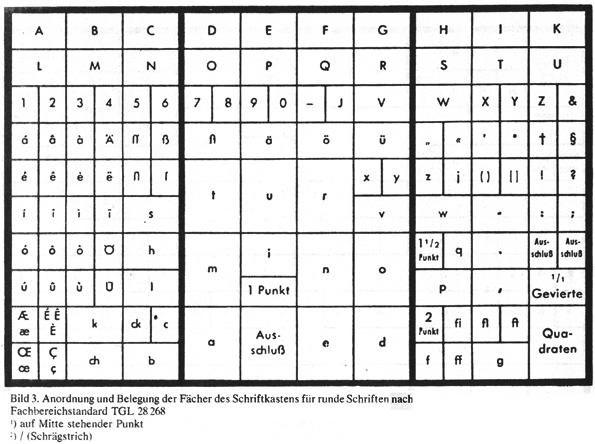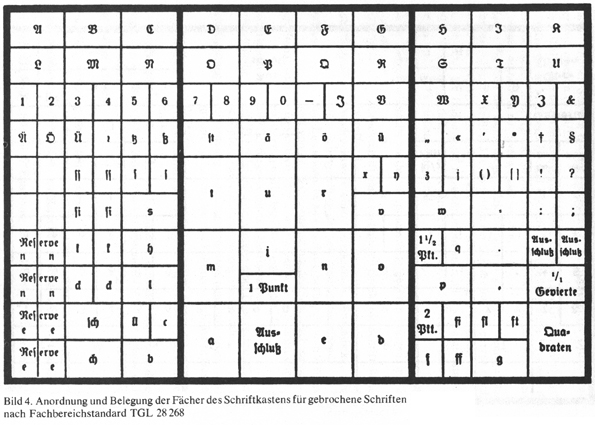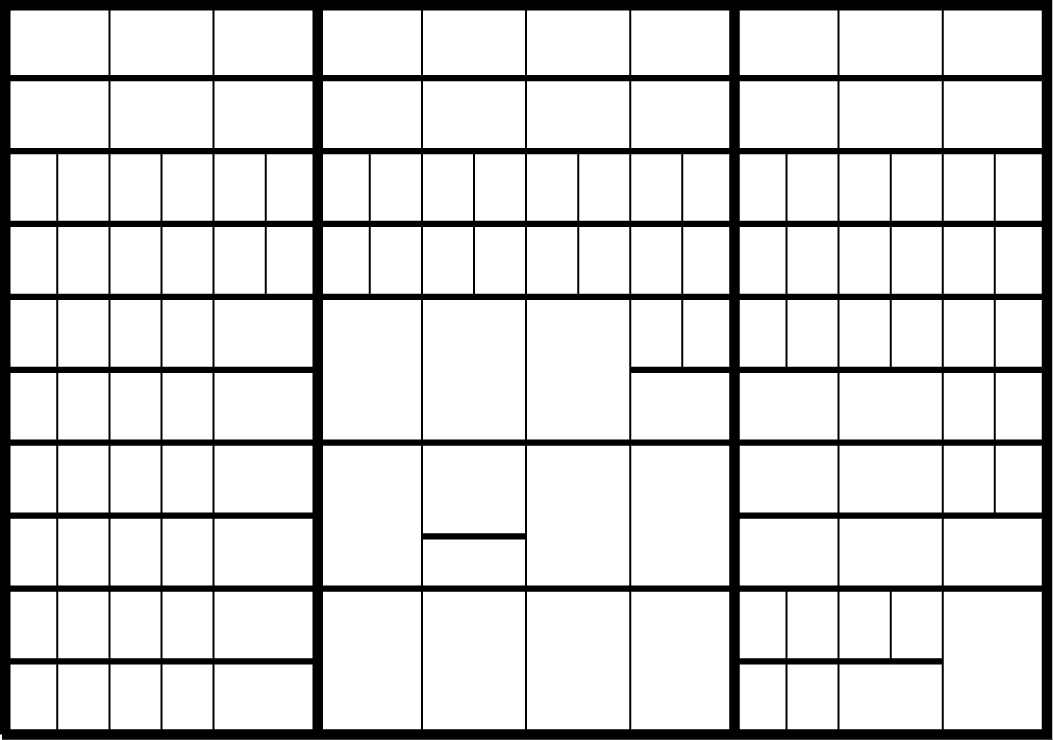
Setzkasten-Layout?
Kleine Frage an die Bleisetzer:
Wie allgemeingültig / verbreitet ist diese Setzkasteneinteilung (Wikipedia) – gibt es da viel Variantenspielraum, evtl. auch zwischen D / CH?
Habe heute im Brockenhaus einen Setzkasten gefunden, für etwa 13 Euro :cheer: .. Und der sieht anders aus als auf dem obigen Schema, siehe Bild. Beispielsweise sind die Kästchen, die im Bild mit »?t«, »ä«, »ö«, »ü« oder auch »W« bezeichnet sind, bei mir nochmal jeweils zweigeteilt; während andere, die im Bild zweigeteilt sind (z.B. 1½-Pt.-Spatium und q), bei mir nur aus einem Kästchen bestehen.
Würd mich interessieren, wenn hierzu jemand Näheres weiß, warum das vielleicht so ist oder so (Mann, ich bin vielleicht manchmal echt zu neugierig). Dranstehen tut übrigens »12 fette Antiqua«, falls das was zur Sache tut.
Grundsätzlich gibt es eine Vielzahl Varianten, auch wenn ich nicht weiß, ob nun ausgerechnet zwischen D und CH (na gut, man muß wohl berükchsichtigchen, daß man in der Chweitz einen gchößerchen Verchbrauch an ch-Ligchaturchen chat, dafür wenigerch ß brchaucht). In der Schweiz wäre weiters zu berücksichtigen, daß es da ja auch andere Landessprachen als das Deutsche gibt, und natürlich hat jede Sprache andere Kastenbelegungen, manchmal sogar eine extrem andere Kastenarchitektur. (Ich habe gerade mal gestöbert und bin erstaunt, was für kuriose Fremdsprachenkästen es doch gegeben hat; ich habe Setzkastenschemata für Sprachen gefunden, von denen ich noch nie etwas gehört habe.)
Und dies ist nur die Theorie. In der Praxis hat es in jeder Setzerei bestimmte Gepflogenheiten gegeben und auch die Setzer selbst haben sich die Kästen an ihre persönlichen Präferenzen angepaßt. Die kleinen Holzstege, die die Fächer unterteilen, sind bei trockener Luft manchmal geschrumpft und einfach aus der Nut gefallen. Als Setzer hatte man einen kleinen Vorrat an solchen Hölzern, mit denen man bei Bedarf Kästen weiter unterteilte. Das ging aber notfalls auch mit zurechtgeschnittenen Regletten oder Bleilinien.
Auch war der vorhandene Zeichenumfang je Schrift unterschiedlich, denn es gab zwar den Normal-Gießzettel, aber eben auch Abweichungen der Gießereien hiervon, die wiederum den Setzer zu individuellen Anpassungen des Schriftkastens zwangen.
Wenn man so ein Arbeiten gewöhnt ist, fallt es natürlich schwer, daß einem heute die Softwarefirmen verbieten wollen, sich seinen Setzkasten nach Gutdünken zu belegen — will meinen: Schriften zu editieren und sich die Zeichen auf die Tasten zu legen, die einem bequem erscheinen.
Übrigens: Wenn man sich z. B. die Frakturschriften der Fa. Delbanco ansieht, wird man feststellen, daß es auch heute abweichende Meinungen über die »richtige« Setzkasten- bzw. Tastaturbelegung gibt. Die haben ein ganz abenteuerliches eigenes Belegungsschema entwickelt. Es ist also alles wie früher: Es gibt eine DIN einerseits und es gibt die Praxis andererseits.
Hier mal Antiqua- und Frakturkasten nach TGL (Technische Güte- und Lieferbedingungen der DDR, sozusagen die Ost-DIN). Man beachte, daß auch im Antiquakasten ganz selbstverständlich ch, ck, Lang-s und die Lang-s-Ligaturen vorgesehen waren (jawoll, Herr Herrmann!).
… man muß wohl berükchsichtigchen, daß man in der Chweitz einen gchößerchen Verchbrauch an ch-Ligchaturchen chat, dafür wenigerch ß brchaucht).
In der Schweiz wäre weiters zu berücksichtigen, daß es da ja auch andere Landessprachen als das Deutsche gibt, und natürlich hat jede Sprache andere Kastenbelegungen, manchmal sogar eine extrem andere Kastenarchitektur.
Das könnte den Unterschied wohl zu einem Großteil erklären. Was interessant ist: Der DDR-Antiquakasten von Dir deckt sich fast ganz genau mit demjenigen aus der Wikipedia. Meiner weicht u.a. in den o.g. Details davon ab, und er sieht nicht so aus, als seien Stege manuell entfernt oder dazugefügt worden (hab leider grad keine Kamera da).
Dann ist meiner vielleicht wirklich ein Schweizer Modell. Zumindest müsste er, der Beschriftung entsprechend, aus einem deutschsprachigen Land kommen.
Mal schauen, ob ich irgendwann einen Schweizer Schriftsetzer kennenlerne, den ich das fragen kann. :)
An meiner Hochschule gabs zwar eine Handsatzwerkstatt, aber wir durften gerade nicht rein. (»Sie sind Multimediadesigner, beschäftigen Sie sich lieber mit der 32-bit-Grafik.« :cry: )
Das ist sehr bedauerlich. Eigentlich sollte ein Grundkurs im Blei Pflicht sein für alle Multimädchendesigner (und die Jungs auch).
… und ichch chattche mirch solche Müche gegchebchen! :(
Was interessant ist: Der DDR-Antiquakasten von Dir deckt sich fast ganz genau mit demjenigen aus der Wikipedia.
Die DDR hat da auch nichts neues eingeführt, sondern nur den Vorkriegskasten in der TGL festgeschrieben, soviel ich weiß. Schriftschaffen und -produktion waren ja recht übersichtlich, man hat also sehr viel mit den Vorkriegsschriften weitergearbeitet. Hatte man z. B. eine alte Englische Schreibschrift, durfte die nur für bestimmte Kunden und nur für kleine Auflagen benutzt werden, um die empfindlichen Überhänge zu schonen. Setzer und Drucker wurden ermahnt, sie nur besonders vorsichtig zu klopfen*.
Nö, es gab beides: An- und eben Abführungen. Bei uns in der Lehrwerkstatt der Kieler Nachrichten lagen die in einem Gefach einträchtig nebeneinander.